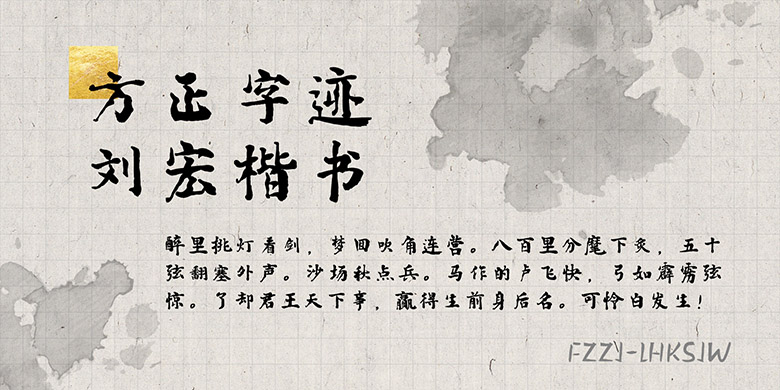
品牌:方正字迹设计师:刘宏发行时间:2018字库编码:简繁扩展(GBK)、大陆简体(GB2312-80)分类:常规书写·毛笔
汉字之美,美在形体,美在风格,美在精髓,美在真情。汉字是民族文化的化石,是历史的载体,是前人智慧的结晶。在每一个方块字中都潜藏着丰富的审美和诗意,有着独特的文化魅力,有着深厚的中国情结。作者刘宏因酷爱书法,致力于书法教学,研究与创作40余载。临颜、柳、欧三体结合,加上自己的创意,书为心画也。